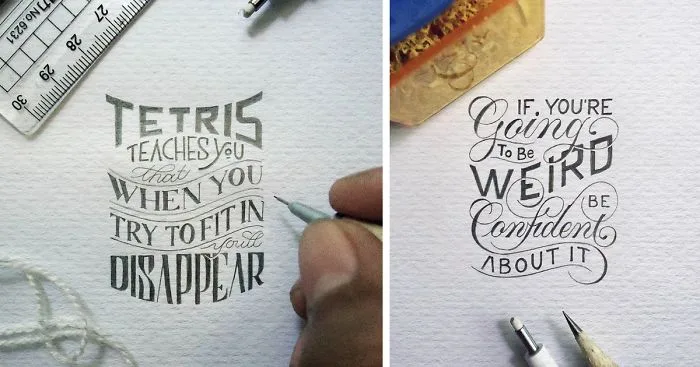
Frases inspiradoras criadas com lindas letras minúsculas
Dexa Muamar é um desenhista que não costuma se categorizar como tal. Atualmente ele estuda para se formar em Desenvolvimento Econômico, mas tem com um de seus grandes hobbys a arte de desenhar.
Recentemente ele tem criado frases com tipografias criativas e bem pequenas, por volta de 3 a 4 centímetros.
Para Dexa as inspirações para suas criações aparecem de diversas partes, seja da família, do dia a dia, da natureza, de tudo ele tira algo para se inspirar e criar suas mensagem e tipografias para cada uma delas.
Dexa não se vê trabalhando com isso, encara o talento como algo somente para momentos de distração, de prazer e nada por obrigação, mas mesmo assim criou um perfil no Instagram para compartilhar suas criações.